中文的圆体字其实是由黑体衍生而来的一种字体,这种字体最早是出现在清朝末期,作为手写体使用,书写较于随意、日常化。经过用字环境不断的变化,圆体的明显特征已经定型为拐角处、笔画末端为圆弧状,字形清晰易于识别字体,端正。
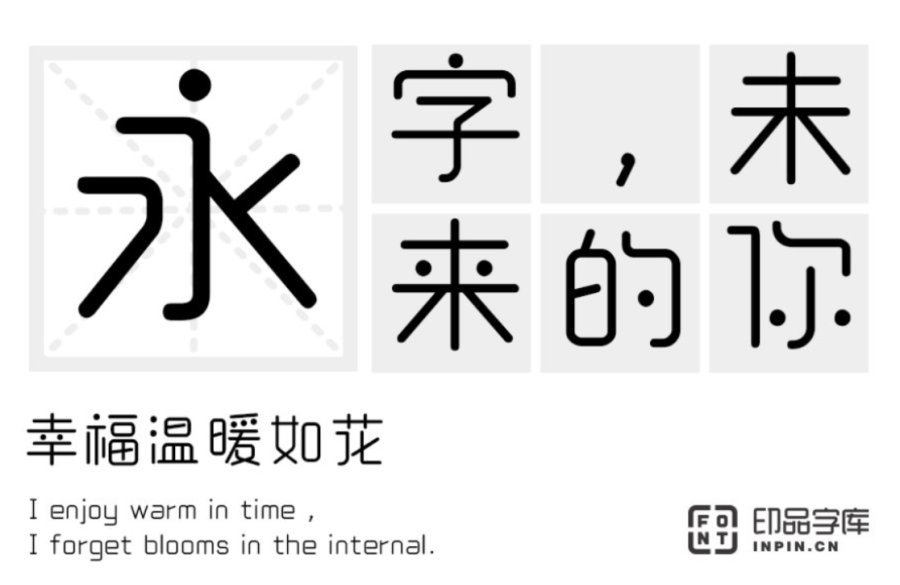
印品睿圆体:这款字体保留了拐角处呈弧形的圆体特点,在字中加入了圆点设计,并且在笔画的走向、粗细及下笔轻重的制作上进行了精心处理,使字体看上去更鲜活、灵动,即保证了美观程度,又不失时尚感。适用于游戏、logo、广告、印刷、包装设计等领域。
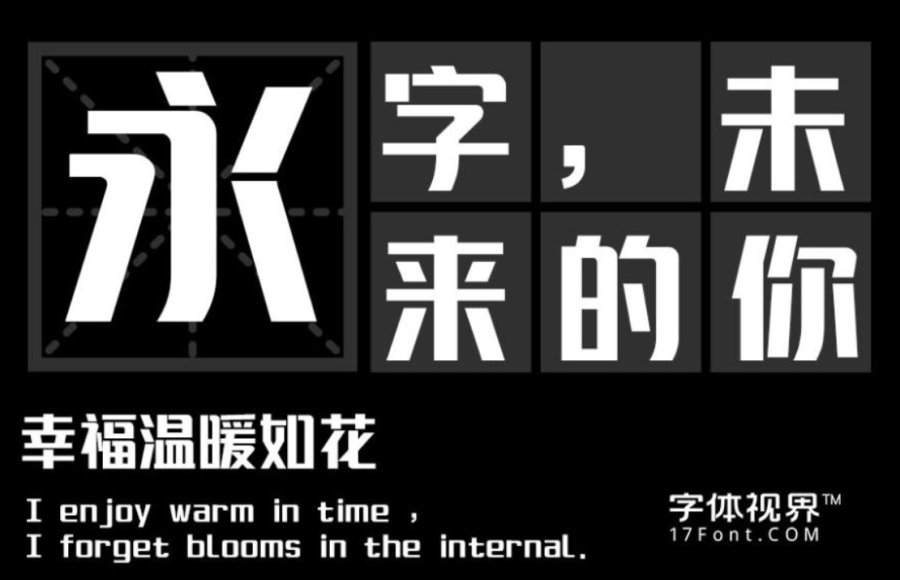
上首锐圆体:这款字体比起传统圆体字体风格锐利偏粗壮,显得庄重,但却在转角处导圆角增添了字体的活跃性,而且字体中有断开处,使字体显得生动灵活。适用于创意设计、标志、印刷、影视、包装设计、PPT标题及正文等领域。
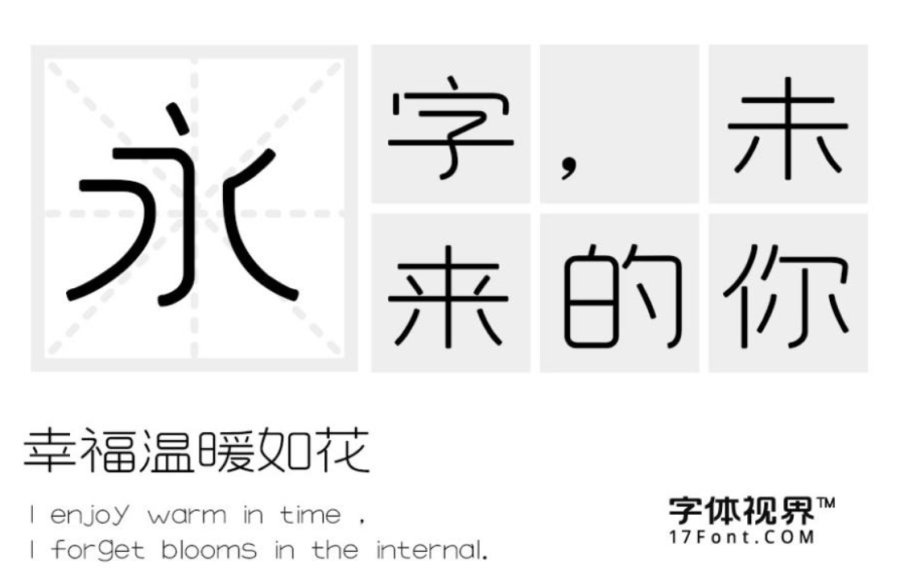
上首秀圆体:这款字体风清新秀丽,笔画瘦长,转角圆润,是此套字库的亮点。从图片字体可以看出上首秀圆体的特征柔和、圆润,具有现代感十足,适用于搭配标志、广告标语、商业广告等高端属性。